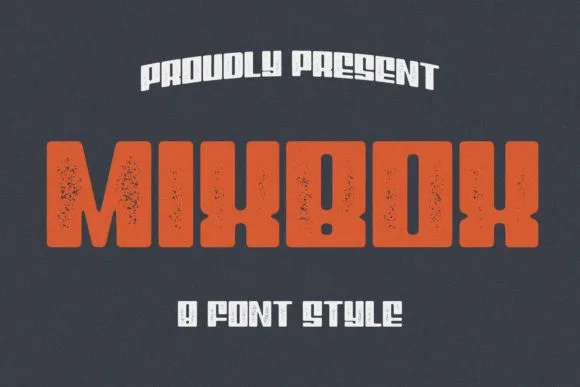
MixBox Font Family – Fonte Grátis
MixBox Font Family
A MixBox Font Family é uma ótima adição para designers que querem trazer um toque vintage ao seu trabalho sem comprometer a modernidade. Inspirada no estilo das impressões antigas, esta família de fontes incorpora linhas rígidas e curvas suaves em perfeita harmonia, criando um visual único e singular. Ideal para capturar o estilismo retro em qualquer projeto futurista, é uma opção ideal tanto para designers profissionais quanto para iniciantes. Esta fonte foi criada pelo designer Sabrcreative e disponibilizada para uso compartilhado. Com seus 8 tipos únicos que compõem a MixBox Font Family, você pode transformar qualquer projeto de design em um destaque imediato. Perfeita tanto para criações de marca, publicidade ou designs de produtos quanto para conteúdos nas redes sociais, essa font é uma escolha perfeita para todos os projetos criativos. Engane-se se acha que esta foi apenas mais uma fonte; ela traz o poder da simplicidade e delicadeza do vintage ao seu trabalho, tornando-a um recurso inegável para qualquer designer gráfico ou profissional de design.